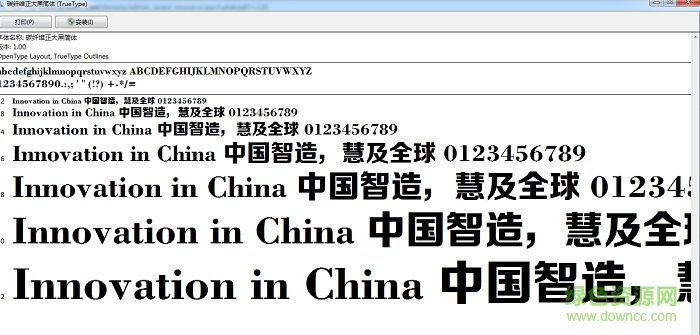
tsin yi ultra是什么字體?tsin yi ultra是一款極具現(xiàn)代感的的文鼎字體,干凈醒目,可用于書、報(bào)、廣告、影視等方面,非常的實(shí)用,讓你在進(jìn)行詞句設(shè)計(jì)時(shí)又能多一項(xiàng)字體的選擇,喜歡的朋友快來綠色資源網(wǎng)下載吧!